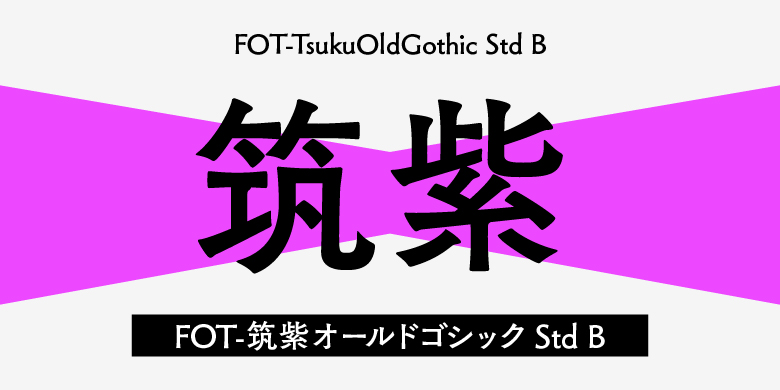
FOT-TsukuOldGothic
金属活字时代似乎存在的哥特体,是一种全新设计的字体。筑紫书体的特点之一是"字体包含的信息量丰富"。这款字体在所有筑紫书体中信息量最丰富,文字本身能够雄辩地表达。纵横画都具有有机的抑扬,紧凑的字体设计在哥特体中展现出最多的风情。仅用汉字单词组合就能明显看出与其他字体的不同。